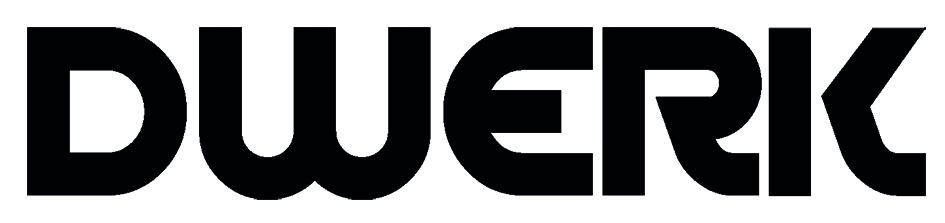
Hallo, ich habe einen Kunden, der sein Logo modifiziert haben will. Ich kann die Schrift auch über die Schrifterkennungsprogramme wie "What the font" und ähnliches nicht finden. Dabei ist sie sehr charakteristisch. Gerade auch das große R und das K.
Hat jemand eine Idee?SCHRIFTtest.jpg.162efa3cb4627fc25927880c6d868ac7.jpg